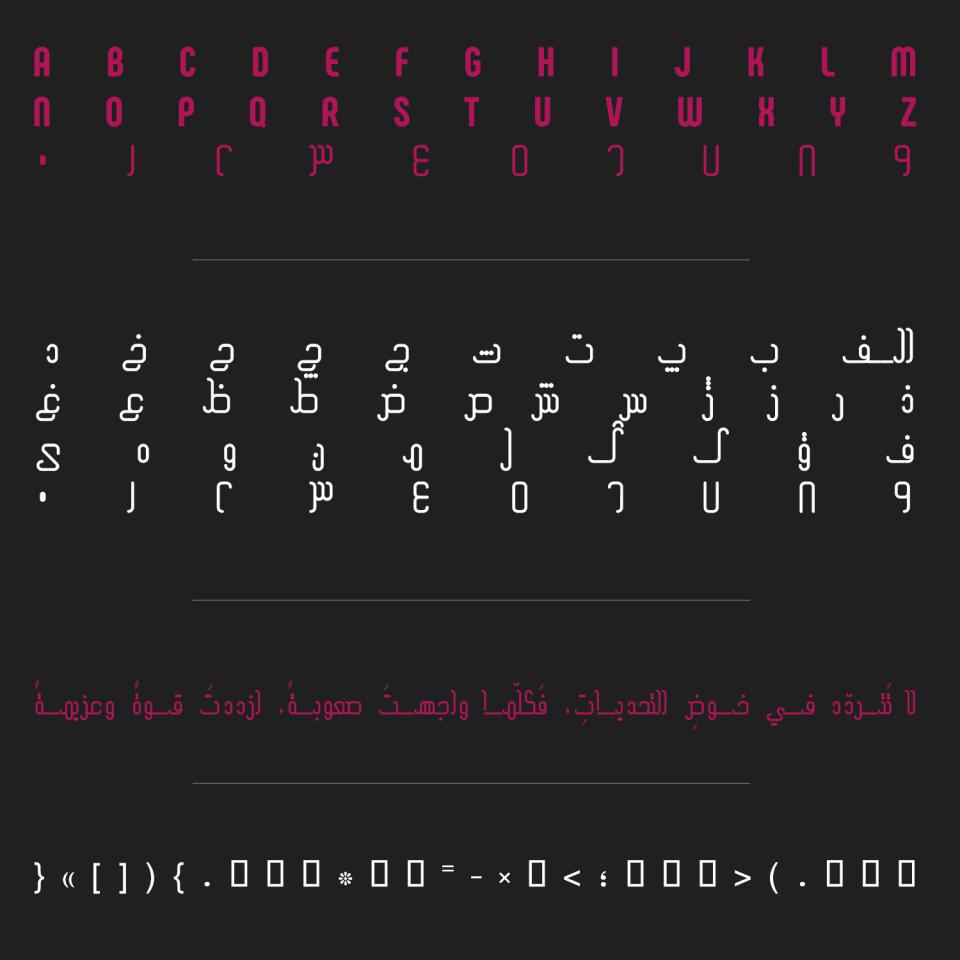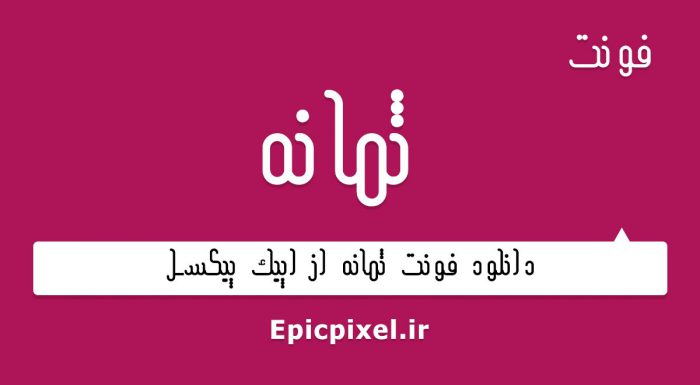
2 فونت سمانه فارسی
فونت سمانه، با طراحی ظریف و خوانا، گزینه ای ایده آل برای پروژه های مختلف شماست. این فونت، با ساختار منسجم حروف، خوانایی متن را در اندازه های مختلف، چه در عناوین بزرگ و چه در متن های طولانی، تضمین می کند. سمانه، با حفظ اصالت خط فارسی، جلوه ای مدرن و جذاب به نوشته های شما می بخشد. این فونت رایگان، به شما کمک می کند تا بدون صرف هزینه، به طراحی های خود، هویتی بصری متمایز ببخشید.
یکی از ویژگی های برجسته سمانه، هماهنگی چشم نواز حروف با یکدیگر است. این ویژگی، باعث ایجاد ریتمی دلنشین در متن می شود و خواننده را به ادامه مطالعه ترغیب می کند. همچنین، طراحی دقیق اتصالات حروف، از گسستگی بصری در متن جلوگیری می کند و تجربه ای روان و لذت بخش از خواندن را فراهم می آورد. این فونت، با پشتیبانی از طیف وسیعی از حروف و علائم فارسی، امکان استفاده در متون گوناگون را فراهم می سازد.
اگر به دنبال فونتی هستید که در عین سادگی، زیبایی و کارایی را با هم داشته باشد، فونت ثمانه انتخابی شایسته است. این فونت، با ارائه ترکیبی متعادل از سنت و مدرنیته، به نوشته های شما، شخصیتی منحصربه فرد می بخشد. رایگان بودن این فونت، فرصتی استثنایی برای طراحان و نویسندگانی است که به دنبال کیفیت بالا با کمترین هزینه هستند.